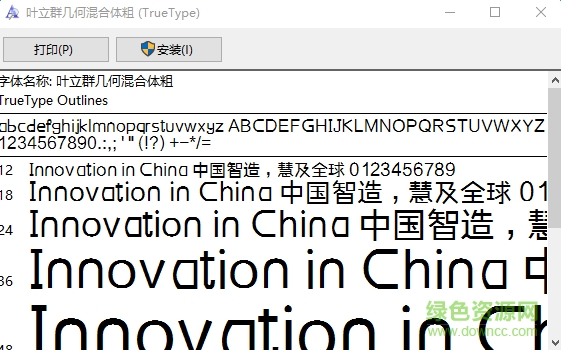
葉立群幾何混合體粗
葉立群幾何混合體粗是葉立群字庫中一款很不錯的粗體字體,這種字體寫出來的字會比一般的字體要粗,但是并不影響它的實用性,依舊可以用于很多方面,歡迎有需要的朋友來綠色資源網(wǎng)下載。
葉立群幾何混合體粗這款字體是真的很不錯的,書本印刷、廣告設(shè)計等都是可以的,大家可以隨時下載使用。